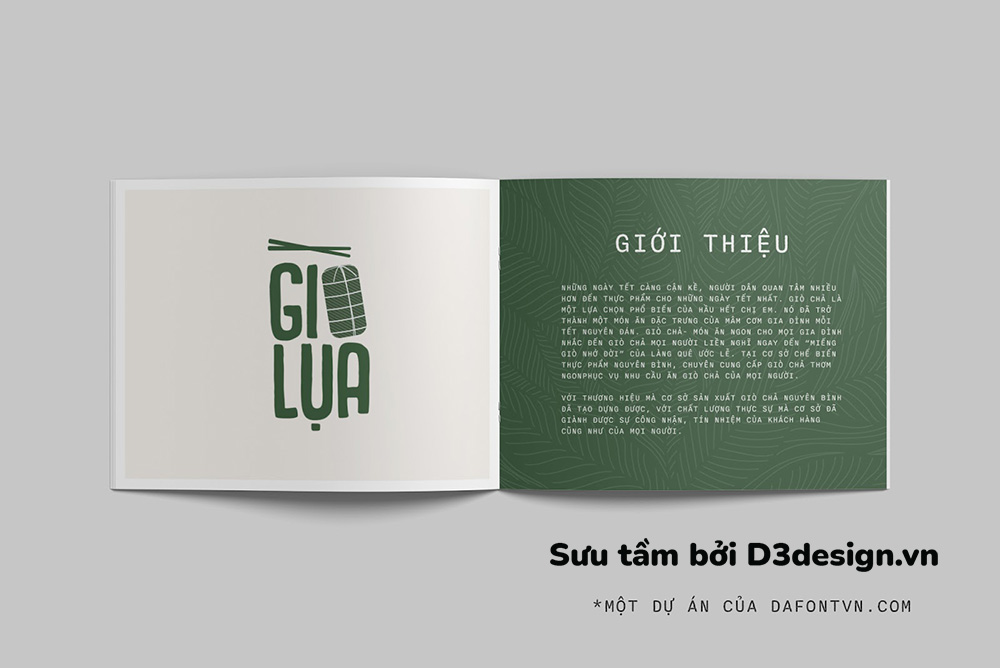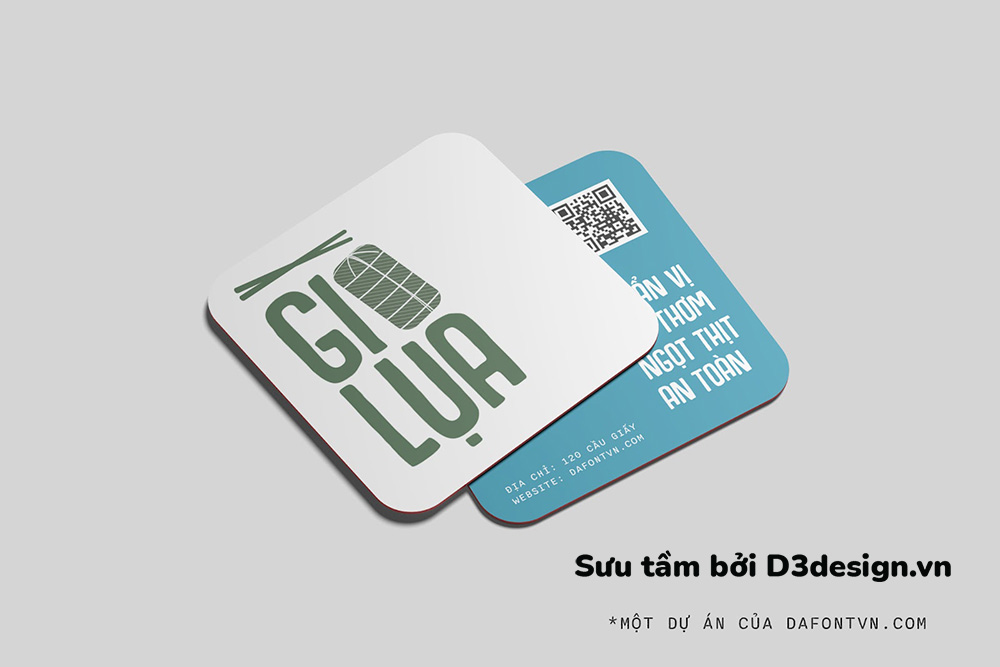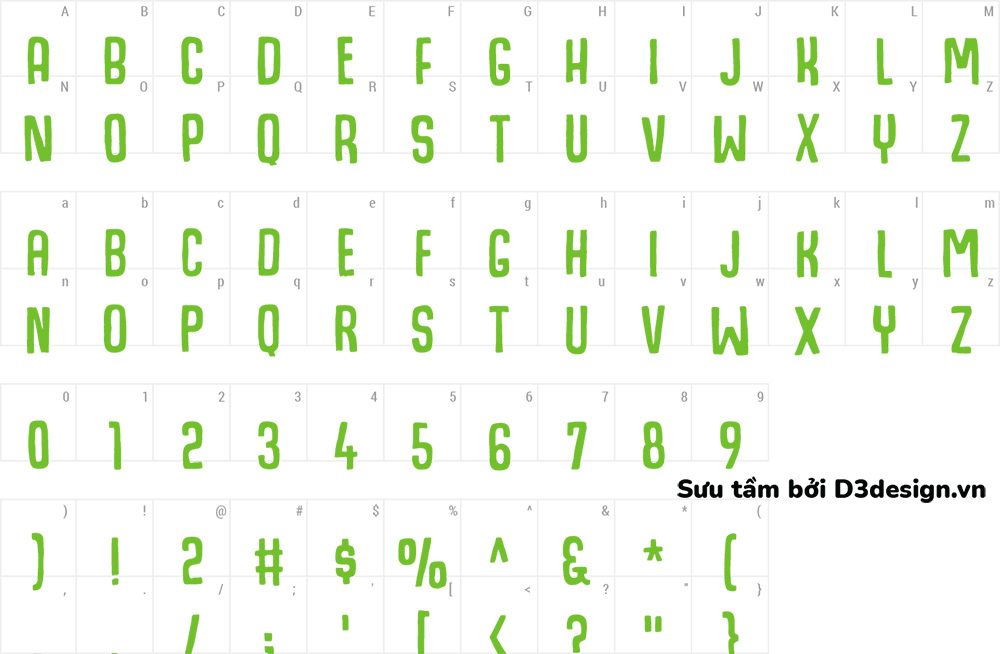
Font Việt Hóa - Hogfish Font Chữ Gây Ấn Tượng
Font Hogfish dù font chữ đã ra đời cách đây khá lâu nhưng font này vẫn phù hợp với rất nhiều thiết kế khác nhau như xây dựng thương hiệu, tạp chí, bìa sách, tiêu đề... Nên dafont đã sẽ chia sẻ lại font này đã việt hóa đầy đủ, kerning và chỉnh sửa lại khá nhiều so với font gốc.